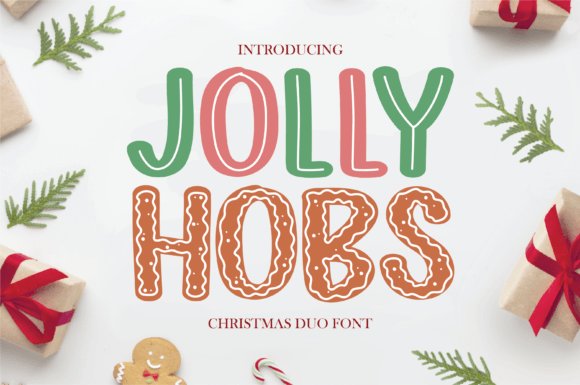
Jolly Hobs Duo
適切なデザイン要素を見つけるのは難しい場合がありますが、Jolly Hobs Duoは作品を即座に引き立てる優れたコレクションを提供します。
POD(オンデマンド印刷)製品、結婚式の招待状、またはソーシャルメディアのグラフィックを作成している場合でも、Jolly Hobs Duoは理想的です。